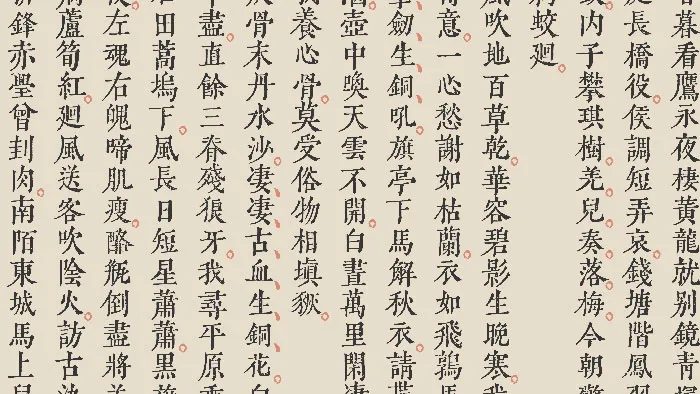
黃令東齊伋復刻體(QIJIC),基於古籍進行處理而得到的字體,所以只有繁體字形,採用半自動計算機視覺和OCR對《李長吉歌詩》和《淮南鴻烈解》進行掃描,通過程序處理後再手動選擇適合的字型,最後導出成字體文件。
在使用字體的過程中,如果輸入簡體字,會直接映射成繁體字形,比如說你輸入“國”字,出來的結果會是“國”字。